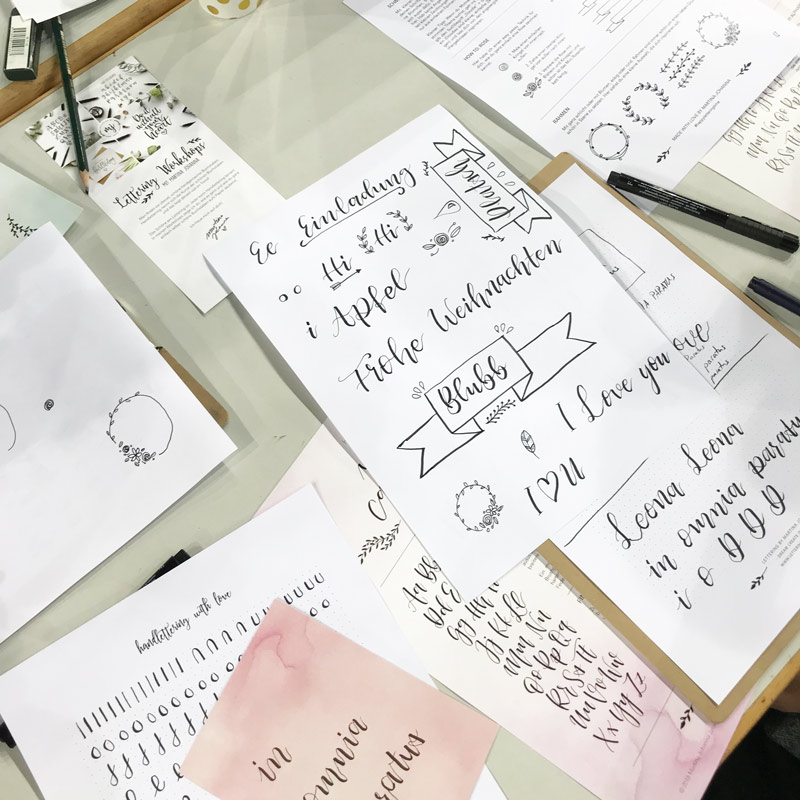
Mein Stand auf der Kreatibzeit in den Messehallen Bremen zum Thema Brushlettering, Moderne Calligraphy
Kreativzeit – Rückblick und Materialliste
Schön war es auf der Kreativzeit in den Messehallen Bremen. Drei Tage lang durfte ich dort kleine Schnupperkurse zum Thema „Brushlettering im modernen Kalligrafie Stil“ geben. Es war unglaublich aufregend und schön, so viele Menschen zu treffen, die Lust auf schöne Buchstaben haben getreu dem Motto: Endlich wieder schön schreiben!
Lettering Workshop auf der Trauzeit und Kreativzeit in Bremen
Hello Hanselife – Kreativzeit in Bremen